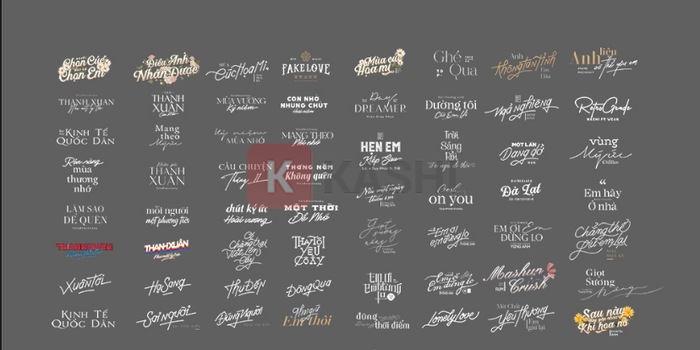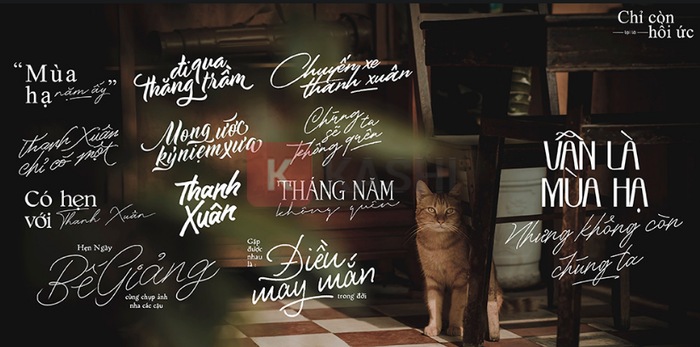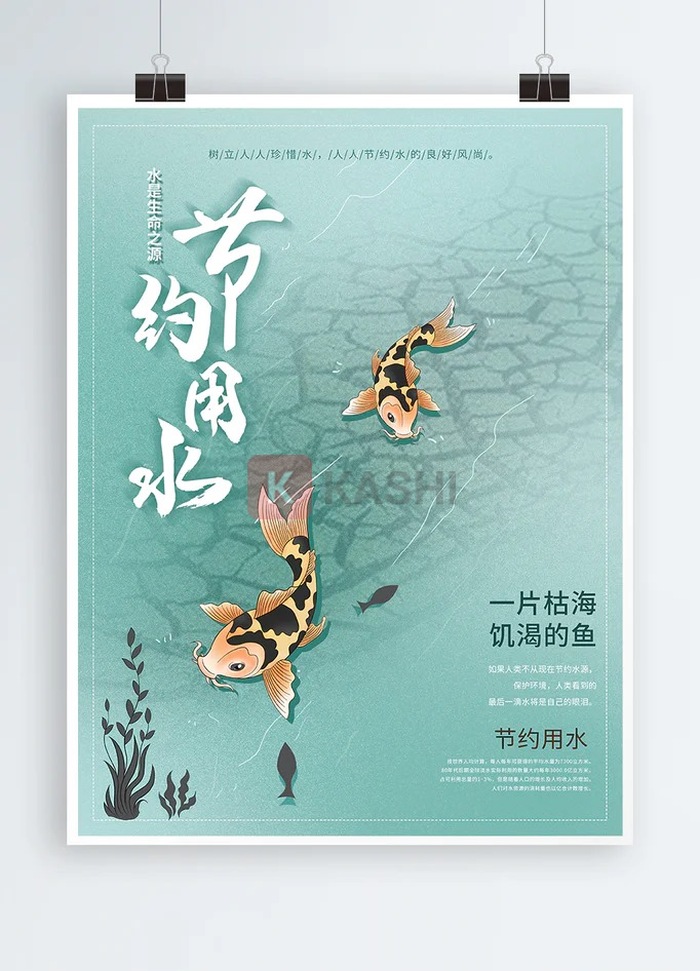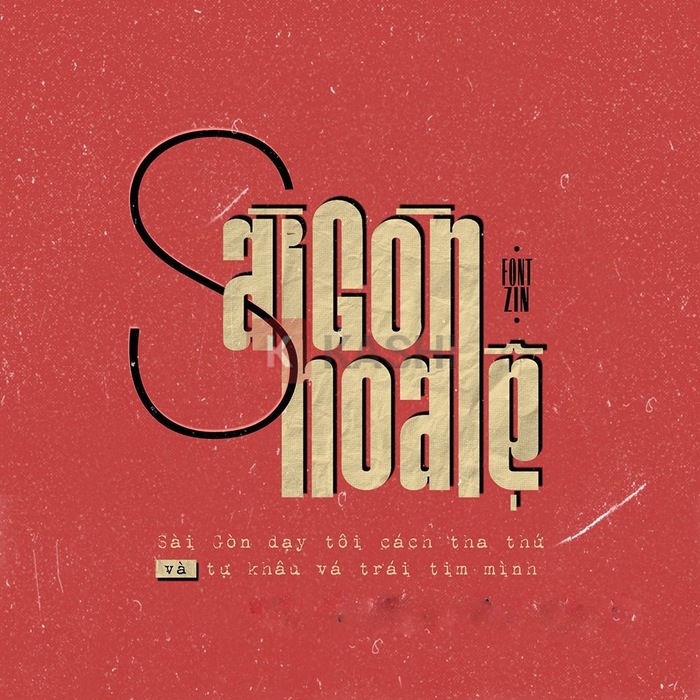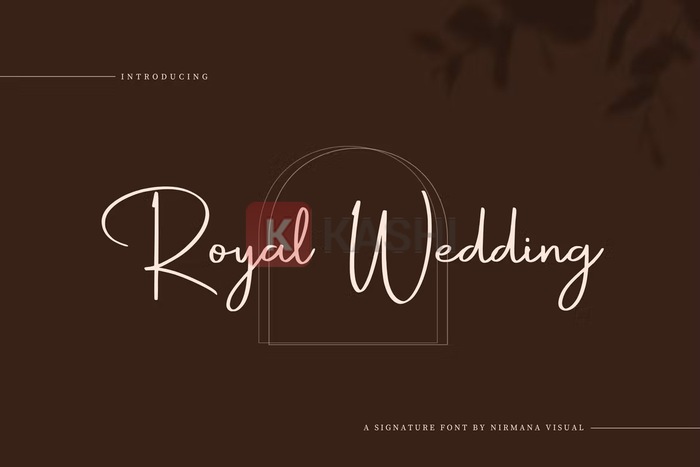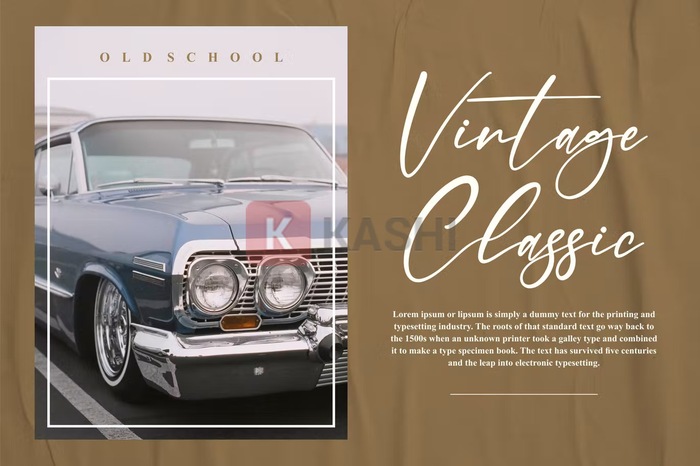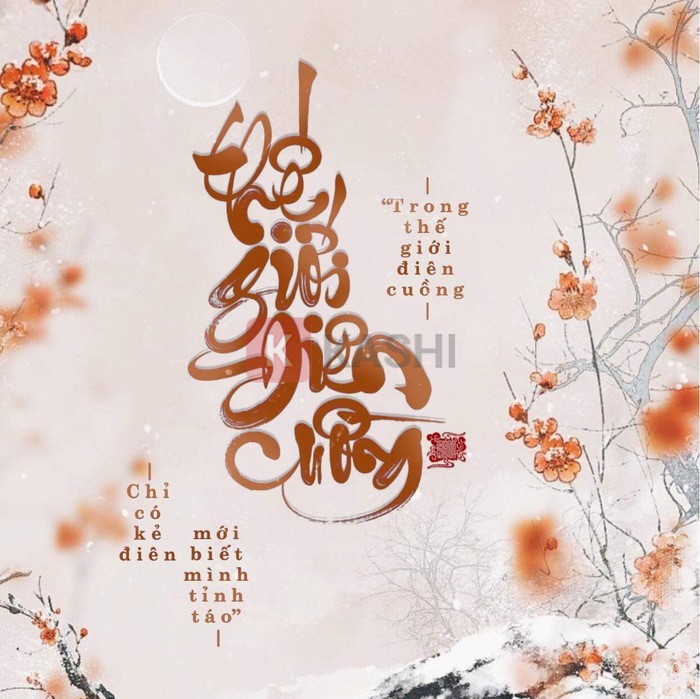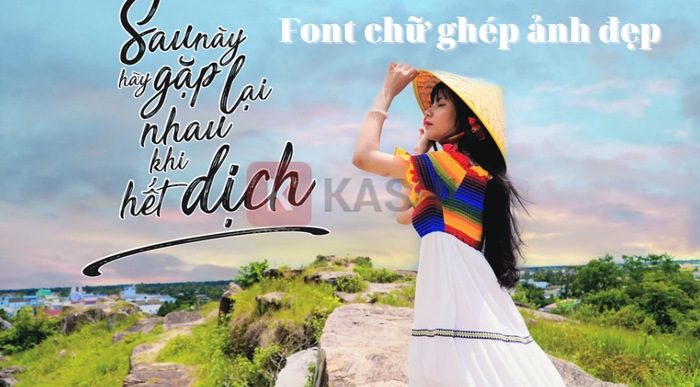
Font Chữ Ghép Ảnh Đẹp, Độc Đáo & Miễn Phí 2025
Bạn muốn tìm kiếm những font chữ độc đáo, ấn tượng để ghép vào ảnh, tạo nên những tác phẩm nghệ thuật typography tuyệt đẹp? Bài viết này sẽ chia sẻ đến bạn bộ sưu tập font chữ ghép ảnh miễn phí, đa dạng phong cách từ cổ điển đến hiện đại, giúp bạn thỏa sức sáng tạo.
Bạn đang tìm kiếm font chữ phù hợp cho ảnh kỷ yếu, ảnh du lịch, hay đơn giản là muốn làm mới những bức ảnh thường ngày? Đừng bỏ lỡ những font chữ tuyệt đẹp được chia sẻ dưới đây. Chúng tôi sẽ giới thiệu đến bạn những bộ font đa dạng, phù hợp với nhiều phong cách và chủ đề khác nhau.
Font Chữ Ghép Ảnh Là Gì?
Font chữ ghép ảnh là những font chữ được thiết kế đặc biệt, thường có kiểu dáng uốn lượn, bay bổng hoặc mang đậm tính nghệ thuật, giúp bức ảnh trở nên thu hút và ấn tượng hơn. Khác với những font chữ thông thường, font chữ ghép ảnh thường mang đến sự độc đáo, mới lạ, tạo điểm nhấn cho bức ảnh và truyền tải thông điệp hiệu quả. Việc lựa chọn font chữ phù hợp sẽ góp phần tạo nên sự chuyên nghiệp và thẩm mỹ cho bức ảnh của bạn.
Typography Trong Thiết Kế
Typography là nghệ thuật sắp xếp và trình bày chữ viết, bao gồm việc lựa chọn font chữ, kích thước, khoảng cách, màu sắc… sao cho hài hòa và truyền tải thông điệp một cách hiệu quả. Typography đóng vai trò quan trọng trong thiết kế đồ họa, giúp tạo nên phong cách và cá tính riêng cho tác phẩm. Mặc dù đòi hỏi kiến thức và kinh nghiệm, nhưng bất kỳ ai cũng có thể làm chủ Typography nếu nắm vững nguyên tắc cơ bản và rèn luyện gu thẩm mỹ.
Top 6 Font Chữ Ghép Ảnh Đẹp Nhất 2025
Việc lựa chọn font chữ phù hợp với bức ảnh là vô cùng quan trọng. Một font chữ không phù hợp có thể làm hỏng toàn bộ bố cục và ý nghĩa của bức ảnh. Dưới đây là 6 bộ font chữ ghép ảnh đẹp và ấn tượng nhất 2025, giúp bạn dễ dàng lựa chọn và sáng tạo.
1. Bộ Typography “Thanh Xuân” (PNG, Đã Tách Nền)
Bộ font “Thanh Xuân” với định dạng PNG đã tách nền, rất tiện lợi cho việc ghép ảnh, đặc biệt là ảnh kỷ yếu hoặc ảnh du lịch. Những mẫu typo này mang đến cảm giác tươi trẻ, năng động, phù hợp với những khoảnh khắc đáng nhớ của tuổi trẻ.
2. Bộ Typo “Chỉ Còn Hồi Ức” (File PSD)
Bộ font “Chỉ Còn Hồi Ức” với những đường nét uốn lượn tinh tế, mang đến cảm giác hoài niệm, lãng mạn. Bộ font này rất phù hợp để ghép vào những bức ảnh kỷ niệm, giúp bạn lưu giữ những khoảnh khắc đáng nhớ.
3. Font Calligraphy Trung Quốc (Việt Hóa)
Bộ font Calligraphy Trung Quốc đã được Việt hóa, mang đến sự độc đáo và mới lạ cho bức ảnh của bạn. Với cả ký tự Latin và tiếng Việt, bộ font này rất linh hoạt và dễ sử dụng.
4. Font Đại Tự Lão Trọc
Font Đại Tự Lão Trọc với nét thư pháp độc đáo, mạnh mẽ, tạo nên sự ấn tượng cho bức ảnh. Bộ font này hỗ trợ đầy đủ ký tự tiếng Việt, bao gồm cả kerning và các ký tự đặc biệt.
5. Font Chữ Phong Cách Sài Gòn Xưa
Bộ font chữ phong cách Sài Gòn xưa mang đến vẻ đẹp cổ điển, lãng mạn, gợi nhớ về một thời đã qua. Những nét chữ uốn lượn mềm mại, tạo nên sự tinh tế và sang trọng cho bức ảnh.
6. Font SCRIPT AND HANDWRITTEN
Bộ 5 font SCRIPT AND HANDWRITTEN với đường nét thanh mảnh, bay bổng, tạo nên sự nhẹ nhàng và lãng mạn cho bức ảnh. Đây là lựa chọn hoàn hảo cho những bức ảnh mang phong cách hiện đại, tinh tế.